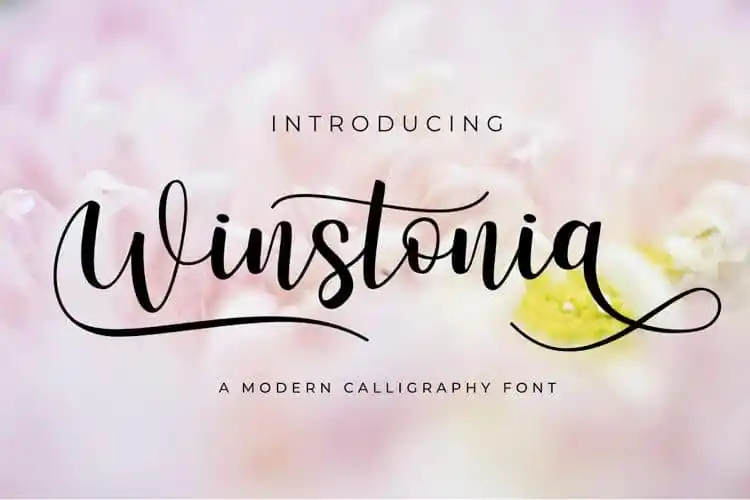
Winstonia Calligraphy Font – Download Grátis
A Winstonia Calligraphy Font é uma elegante tipografia escrita à mão projetada para aperfeiçoar qualquer projeto design. Perfeitamente adaptada a anúncios de casamento, cartões de agradecimento, citações e cartas de cumprimentos, ela também se destaca em logotipos, cartões de visita e qualquer outro trabalho gráfico que necessite de um toque único e autêntico da mão. Em seu estilo fluido e sofisticado, esta fonte atinge a perfeição, tornando-a uma escolha indispensável para designers e criadores buscando aquela sensação única de escrita à mão em seus projetos digitais. Com Winstonia Calligraphy Font, você pode trazer um toque autêntico e personalizado aos mais variados tipos de trabalhos design.